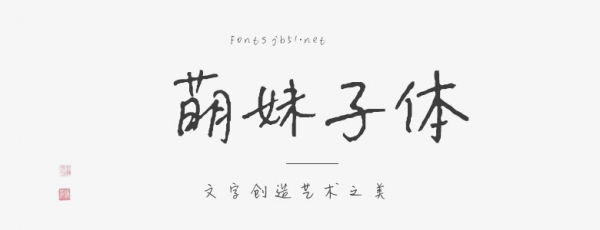
萌妹子體很明顯就是萌妹們都喜歡的字體,這款字體是一款手寫字體,有些飄逸但是又帶些童真俏皮,它的中文和英文有粗細之分,英文比較細,中文比較粗,整體看來很具有觀賞性。
萌妹子體是一款適用性非常廣泛的中文字體,該字體以稚童學字之筆意為基本設計理念,結構松散有度,處理靈活多變、錯落有致,散亂錯落處盡顯質樸幼拙、天真爛漫之意趣,能夠應用于文本裝潢、信息展示、網頁設計、篆刻制模、數據制作、裝潢設計、計算藝術設計、視覺設計、字帖等一切合法應用場景。